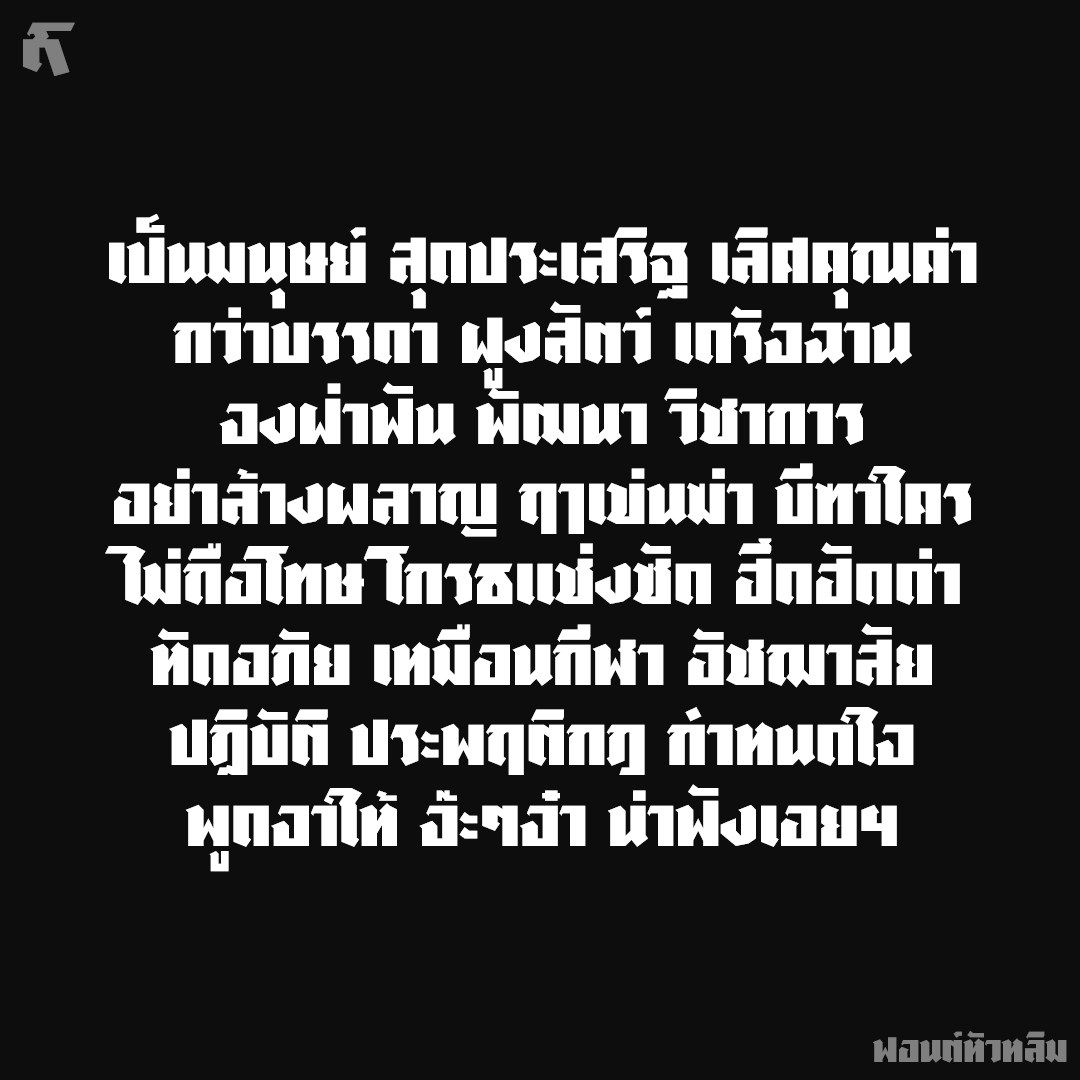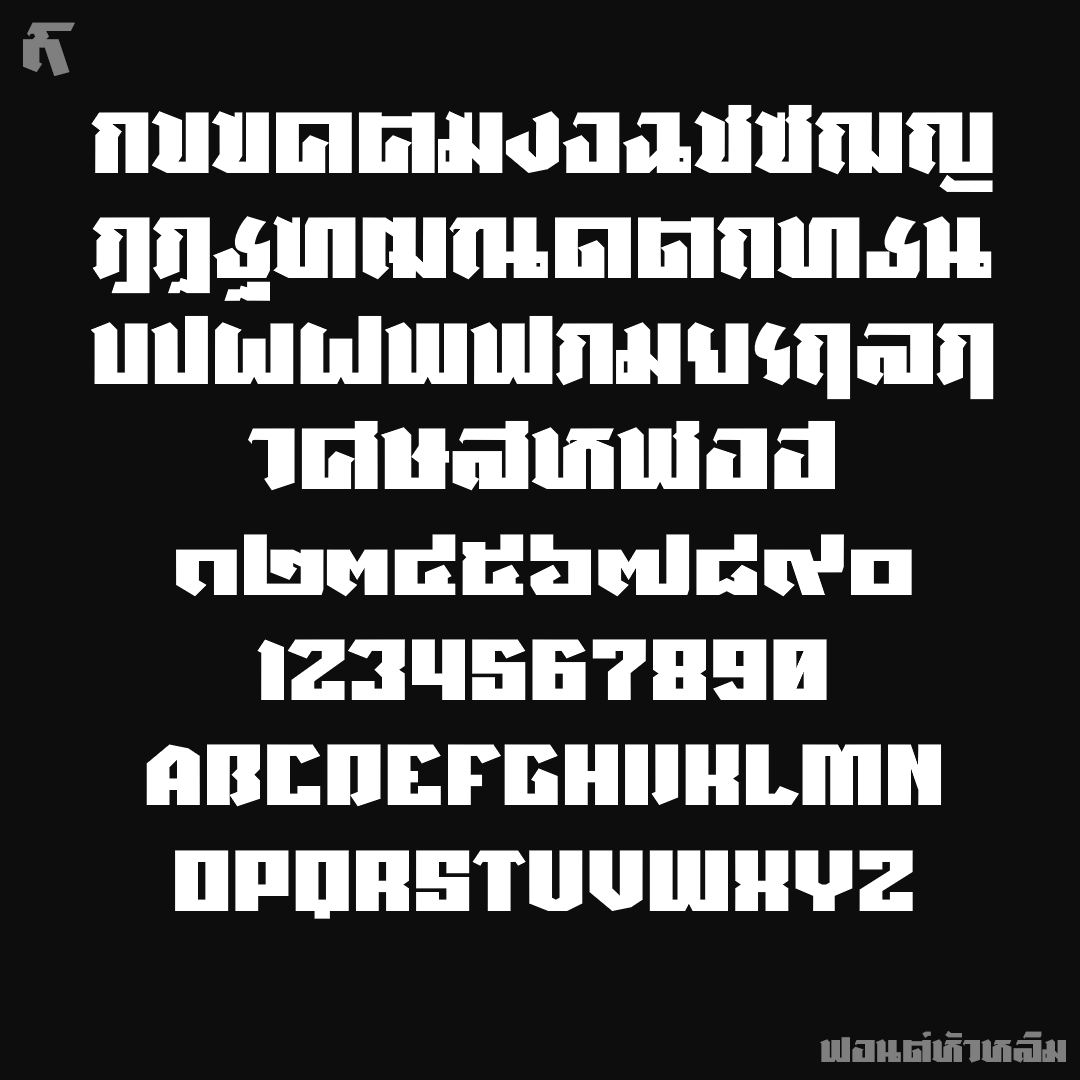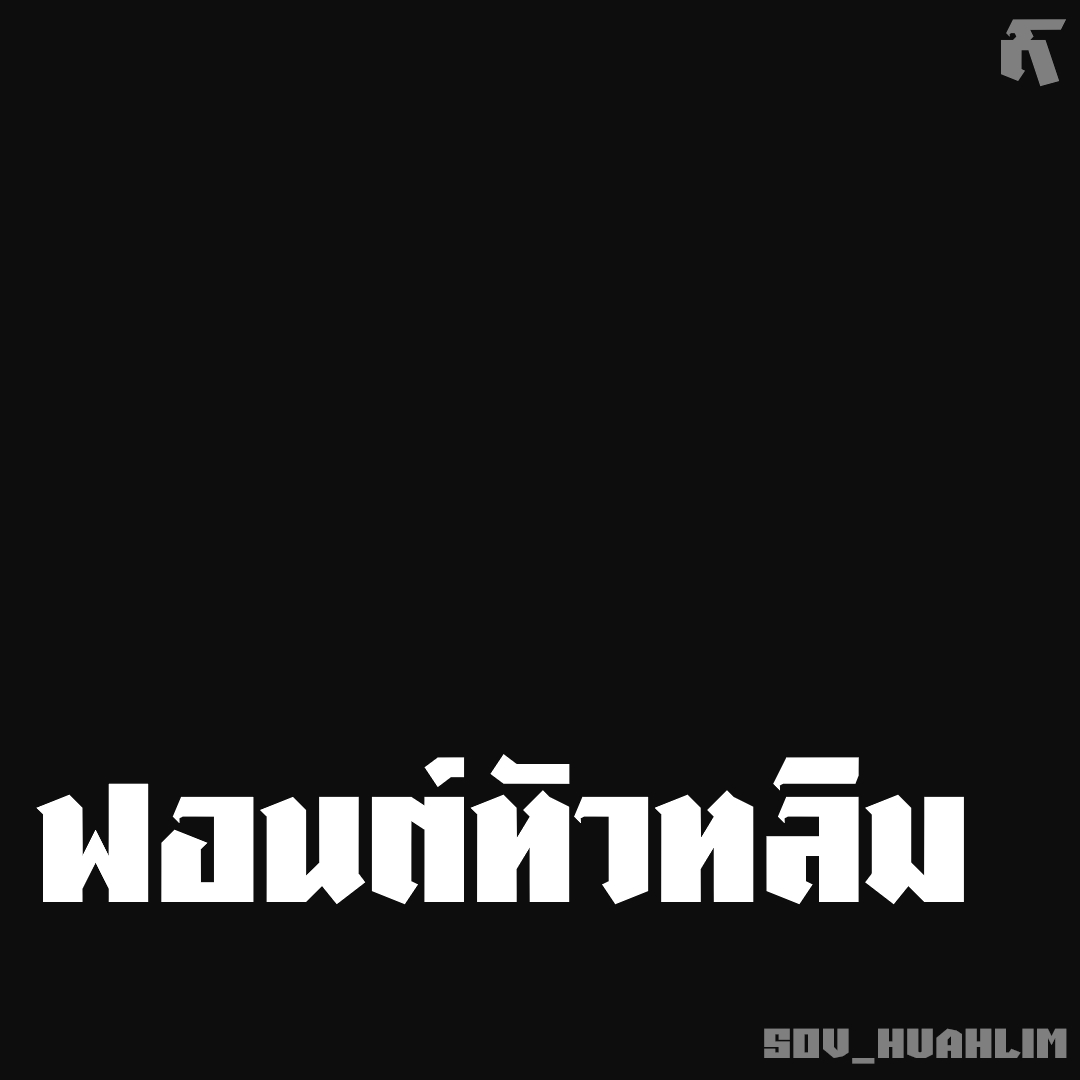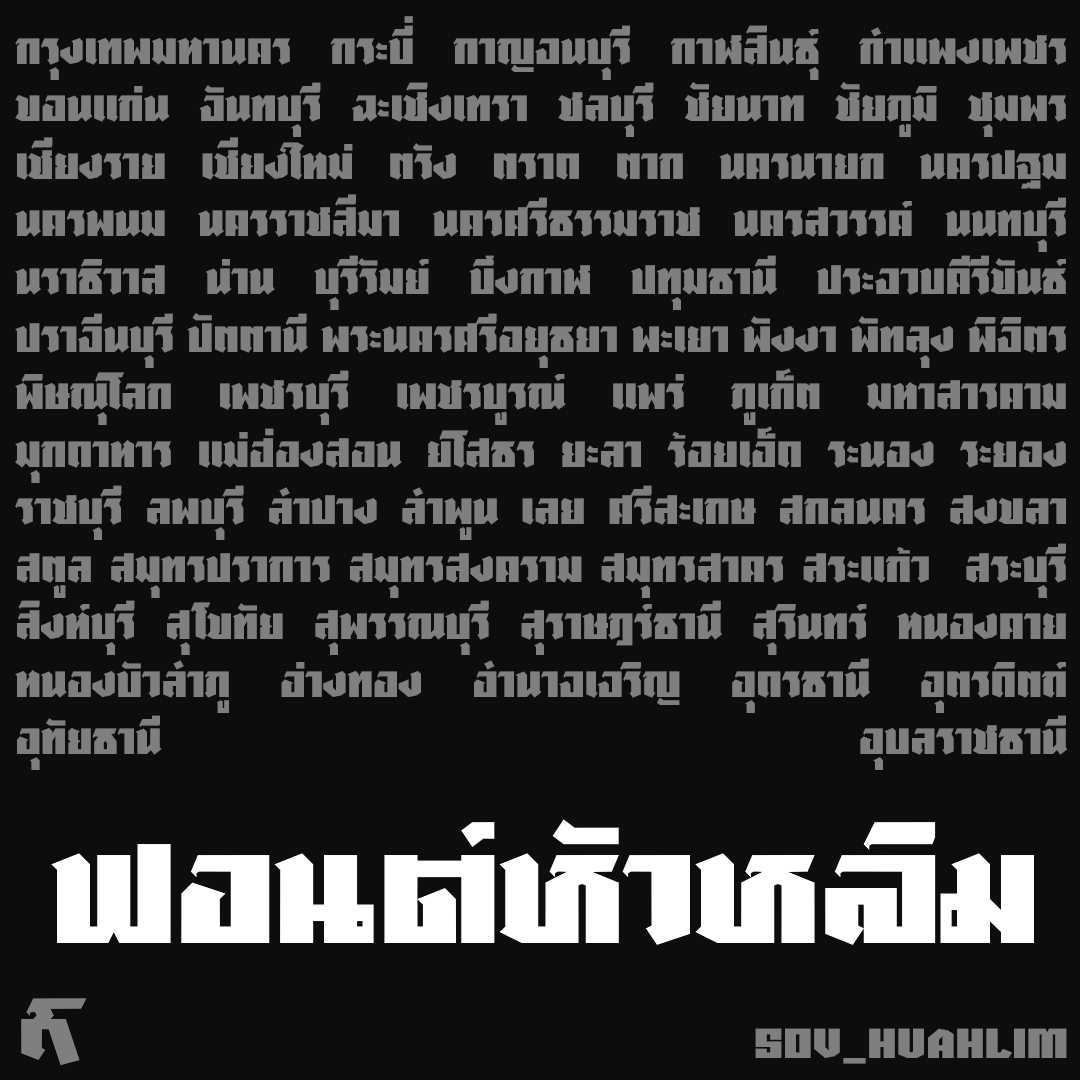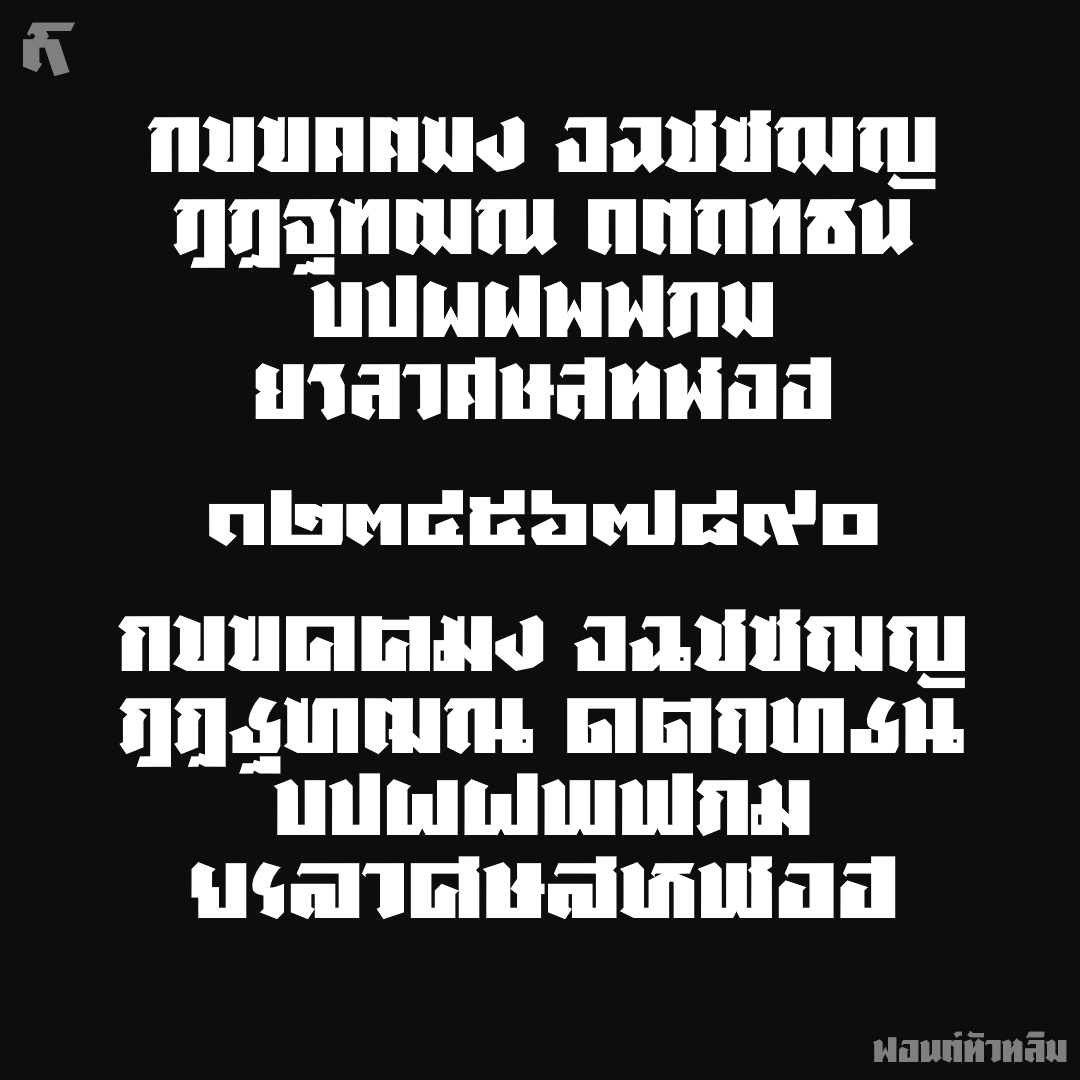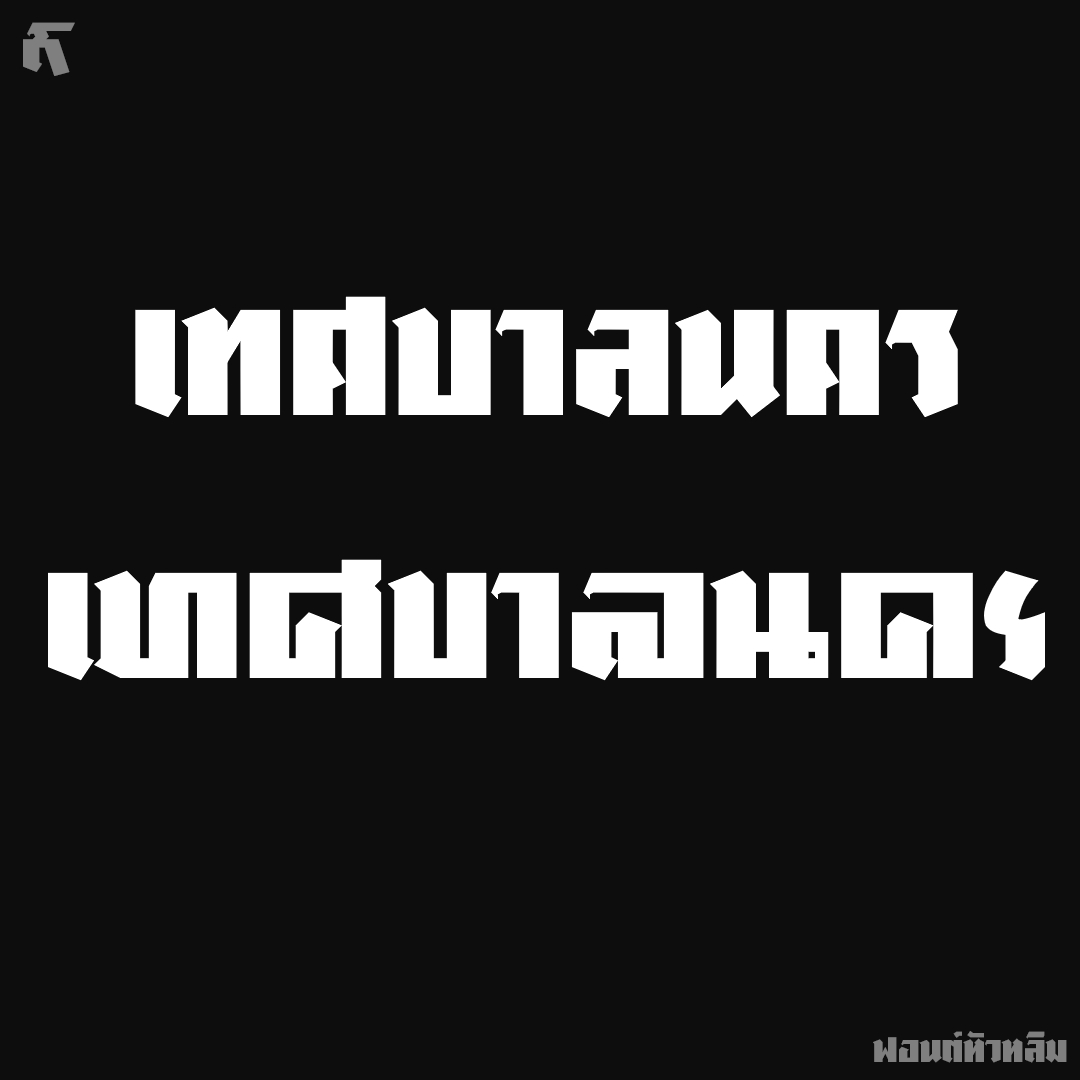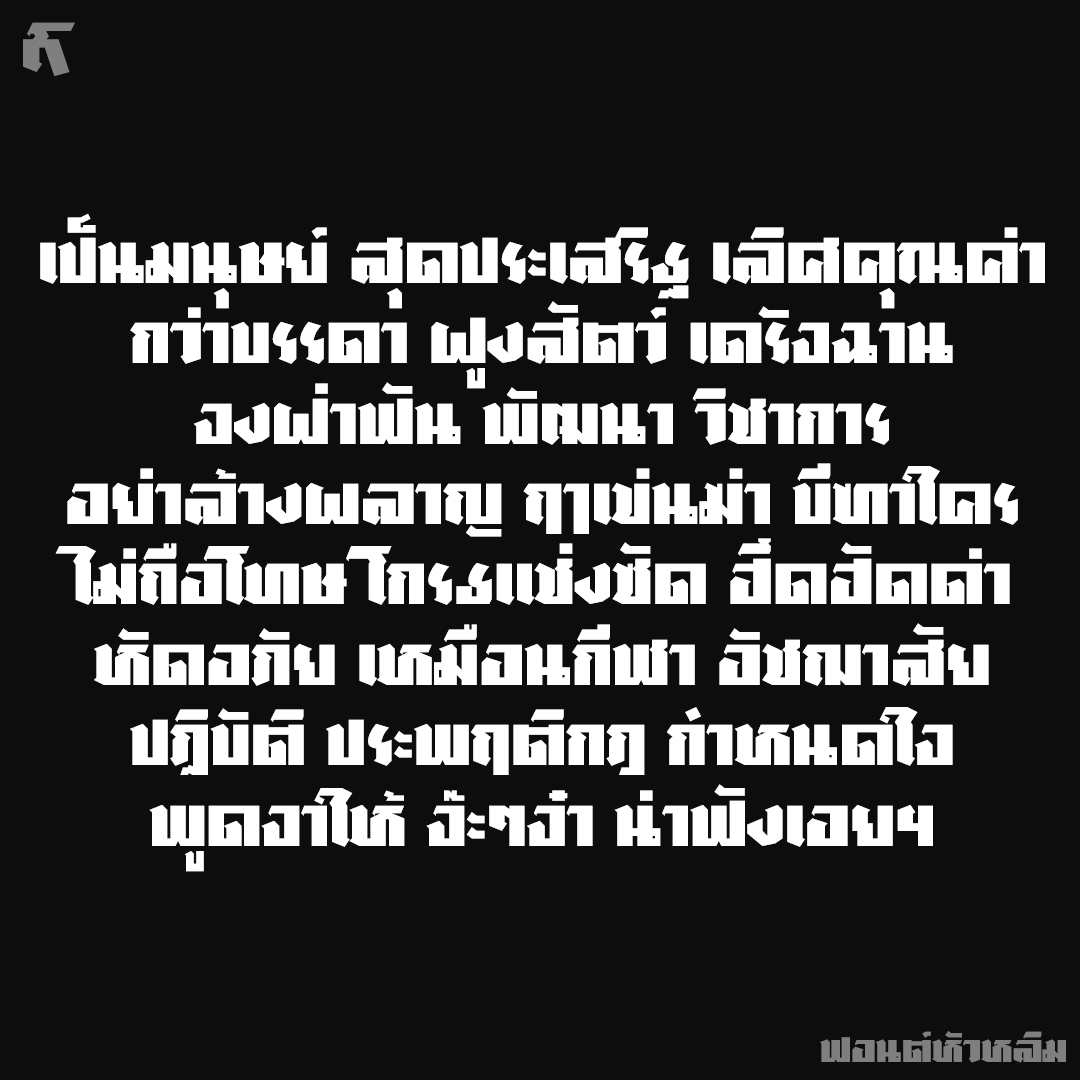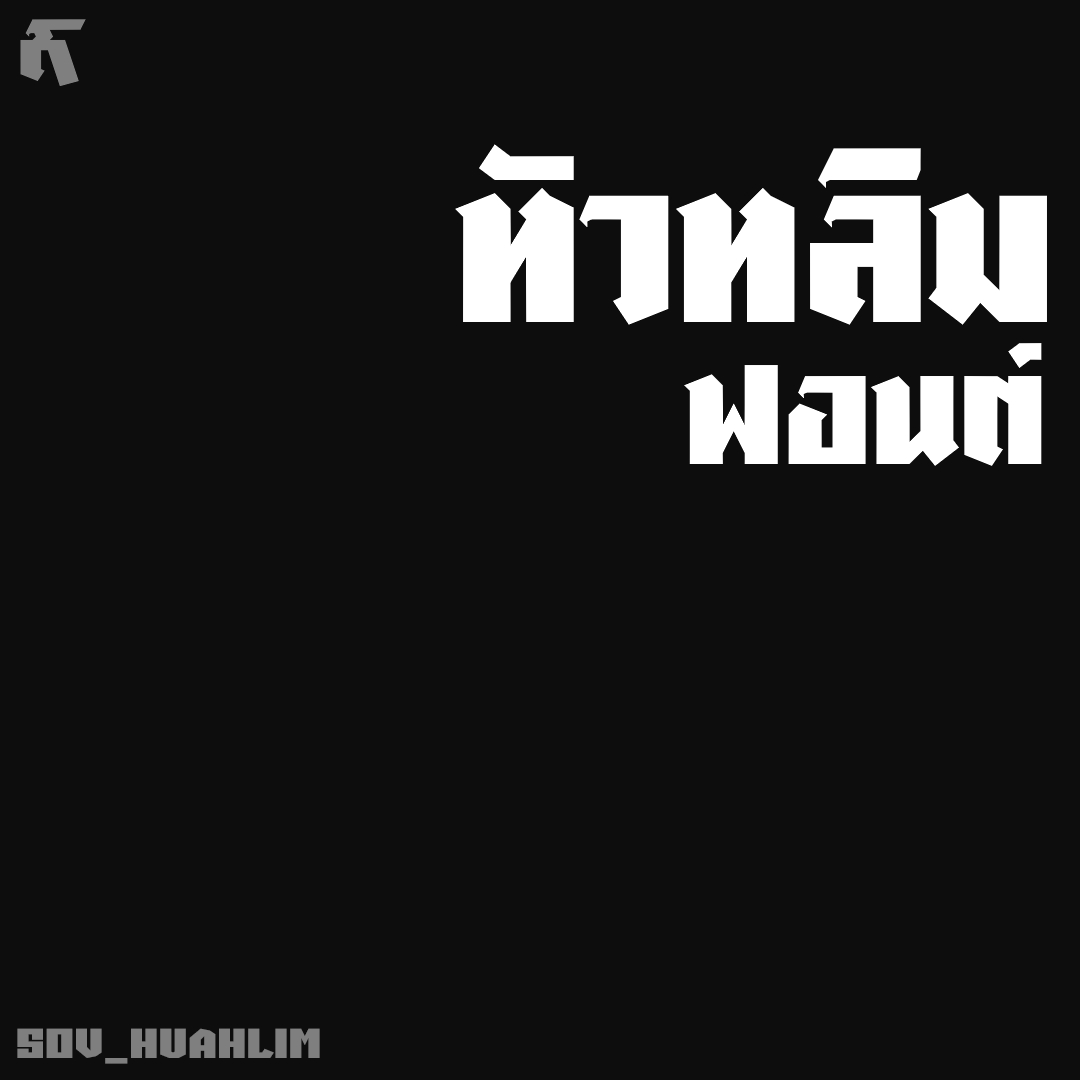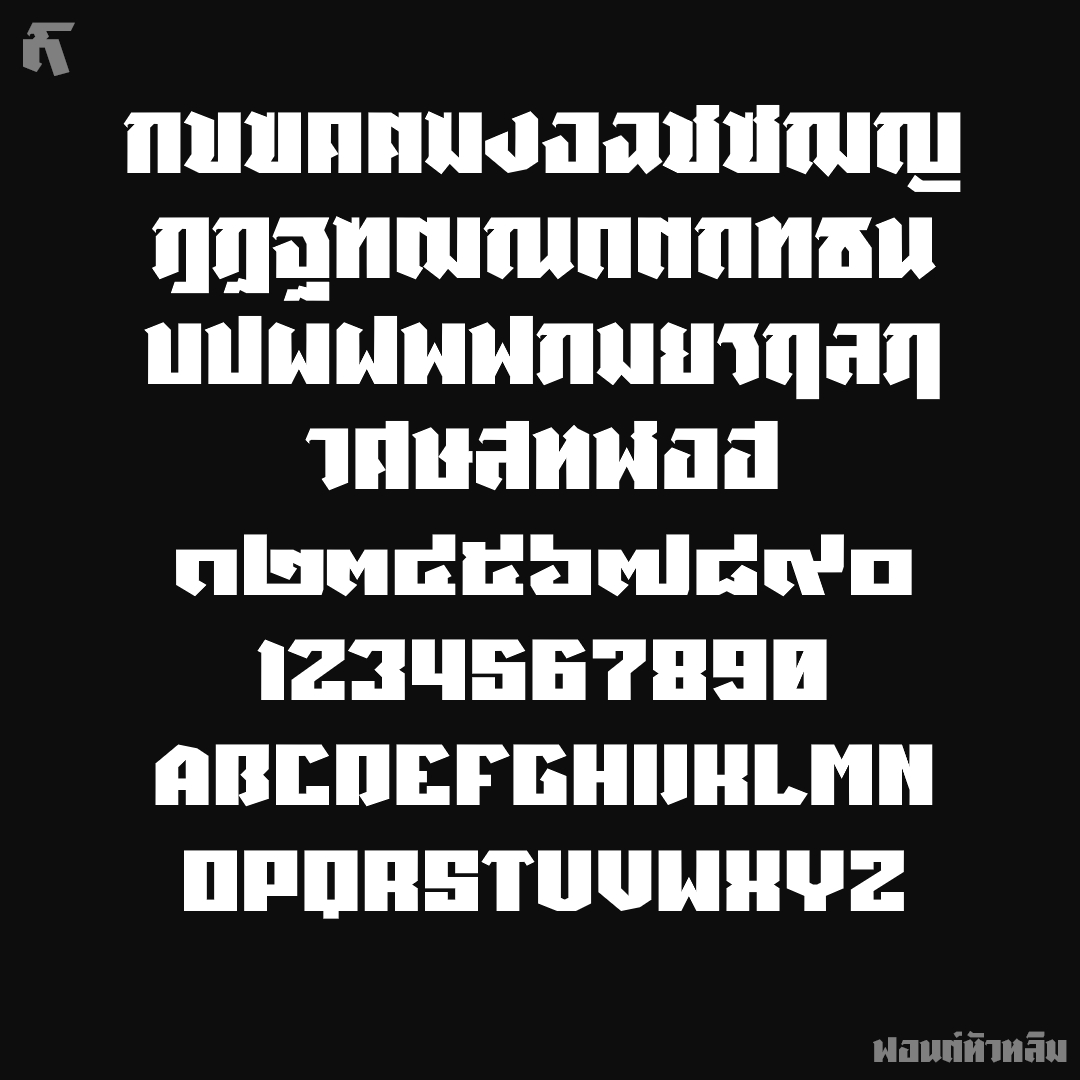
ฟอนต์ หัวหลิม
แนวทางจากปกนิตยสาร และป้ายที่พัก ตัวอักษรมีหัวหักมุมเล็กๆมีมุมแหลมนิดๆ ขออนุญาตเรียกฟอนต์หัวหลิม ส่วนตัวอักษรปรกติสองเส้นตั้ง ตัวหนาสามเส้นตั้ง
ชื่อฟอนต์ : หัวหลิม
แนวทางจากปกนิตยสาร และป้ายที่พัก ตัวอักษรมีหัวหักมุมเล็กๆมีมุมแหลมนิดๆ ขออนุญาตเรียกฟอนต์หัวหลิม ส่วนตัวอักษรปรกติสองเส้นตั้ง ตัวหนาสามเส้นตั้ง